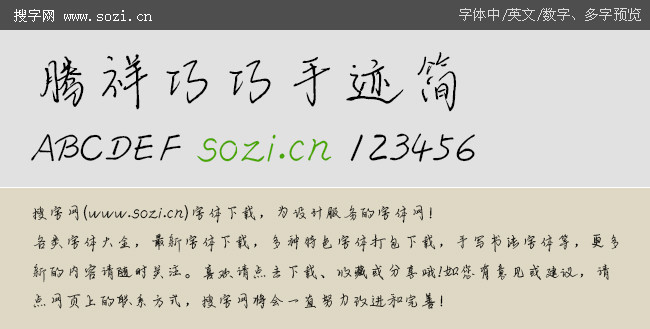
騰祥巧巧手跡簡
搜字網(wǎng)提供一款騰祥巧巧手跡簡中文藝術字體下載,騰祥巧巧手跡簡是一款很漂亮的手寫字體,書寫風格自然流暢,獨具風格,稚拙中透顯出活潑靈動的氣息;無雕琢,無拘束質樸的視覺效果,用于正文更體現(xiàn)出手寫自然之感。字體可以廣泛應用于印刷出版、包裝設計、廣告設計、網(wǎng)頁設計等領域。